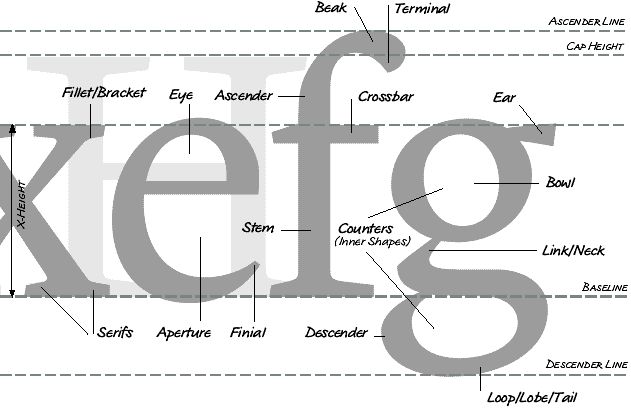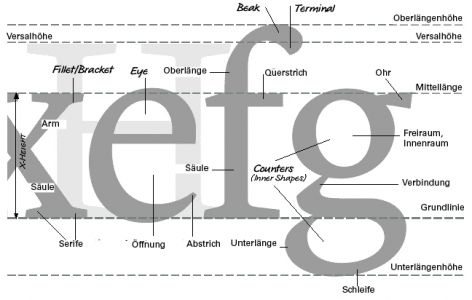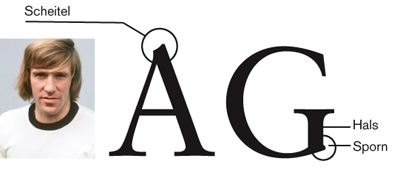
Typographische Fachbegriffe für einzelne Buchstabenstücke
Ich habe meinen heutigen Abend damit verbracht Fachbegriffe herauszufinden wie z.B. Punze, Serife, Grundstrich, x-Höhe usw. Dabei haben mir einige Bücher und eine Übersetzung von Manuel Bieh des Typeworkshops von Underwear schon sehr weitergeholfen. Er hat auf seine Seite dazu auch einige Links gestellt wie z.B. diese hier: http://www.typolexikon.de/ und diesen: http://gmunch.home.pipeline.com/typo-L/faq/anat.htm
Bei ersterem habe ich ein kleines Verständnisproblem, weil dort kein Pfeil auf die entsprechende Stelle des Buchstabens zeigt. Beim zweiten wäre das ja perfekt! Allerdings bräuchte ich diese Begriffe auf Deutsch.
Wenn mir jemand helfen könnte, mit einem Link wäre ich sehr dankbar! Wenn nicht wäre es toll, wenn mir jemand anhand von einigen Buchstaben noch einige weitere Begriffe erläutern könnte und evtl. auch etwas dazu sagen, weshalb man all diese „Schnörksel“ an die entsprechenden Buchstaben anfügt!
Hier ein erster Hilfeansatz, so aus der Erinnerung, unvollständig, ohne Gewähr :oops:
Freiraum/Innenraum = Punzen
Öffnung = Offene Punze
Der Innenraum eines e heißt auch Punze obwohl es auf Englisch „Eye“ heißt, ebenso der Innenraum der g-Schleife bzw. der Innenraum des g selbst? Oder hat die e-Punze doch einen speziellen Namen?
Könnte das was beim f „Break“ bzw. „Terminal“ heißt auf Deutsch ein Tropfen sein wie beim r?
Arm bzw. eine Säule gibt es dann z.B. auch beim w, richtig?
Ja, das hab ich gelesen. :wink: Ich hatte mich nur gefragt, ob alle Innenräume generell Punze genannt werden oder ob sie je nach Buchstabe bzw. Form noch einen spezielleren Namen haben. Ich hoff du verstehst was ich meine.
Nicht zu vergessen:
Sehr gut! Den buchstäblichen Fachbegriff werde ich nicht mehr vergessen (das waren noch Frisuren ...). Aber ich tät' mich jetzt schon wundern, wie Hals und Sporn zu versinnbildlichen wären. Porträt Cäsars auf dem Kopf stehend? Rudi Carell?
Könnte das was beim f „Break“ bzw. „Terminal“ heißt auf Deutsch ein Tropfen sein wie beim r?
Ganz genau.
Arm bzw. eine Säule gibt es dann z.B. auch beim w, richtig?
In Antiquaschriften ist das so – der dickere Strich ist die Säule.
ob alle Innenräume generell Punze genannt werden oder ob sie je nach Buchstabe bzw. Form noch einen spezielleren Namen haben
Punzen sind Buchstaben-Innenräume im Allgemeinen.
Manche haben dann noch Namen, wie eben das Auge beim e.
Da gibt es aber kein wirklich offizielles Vokabular.